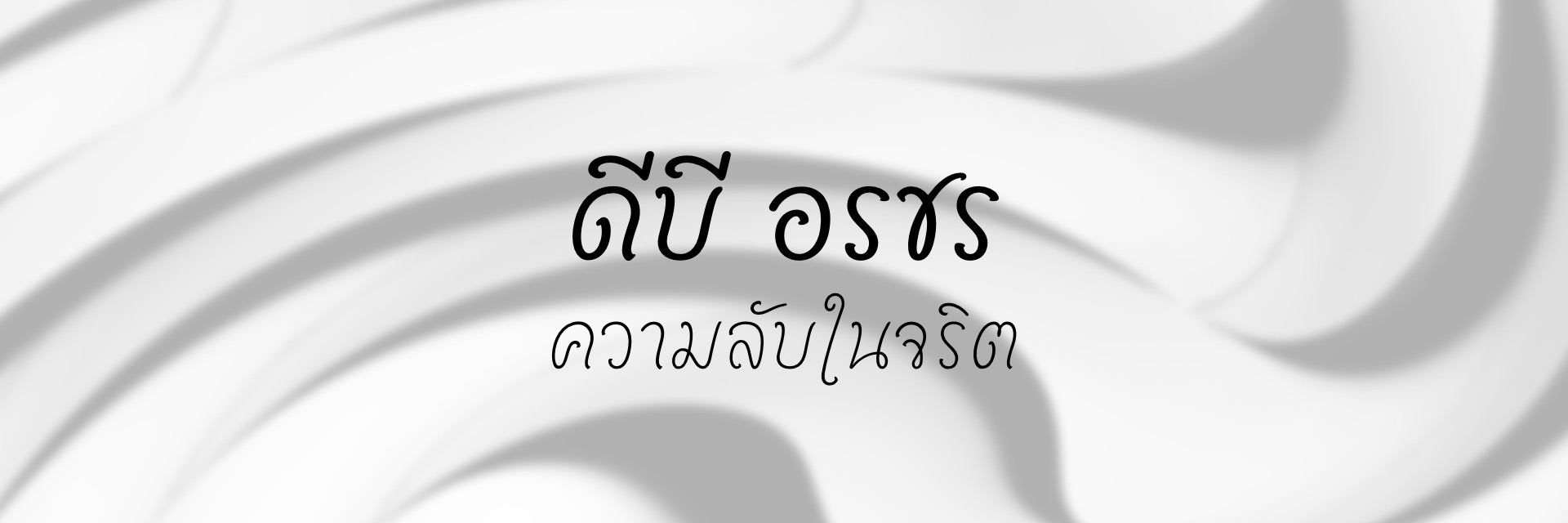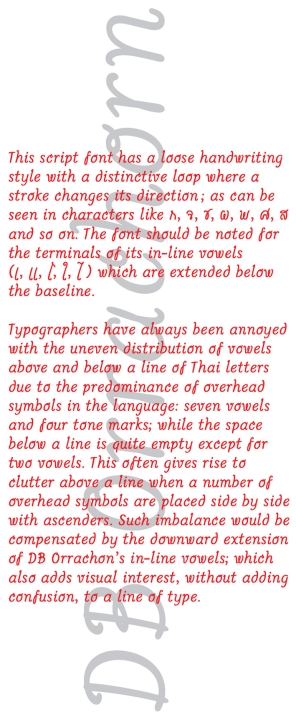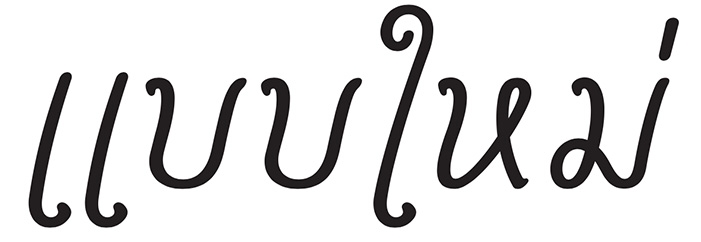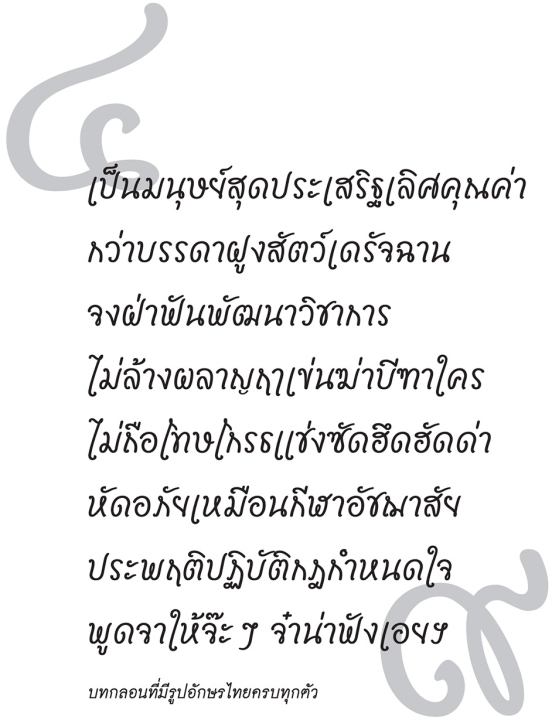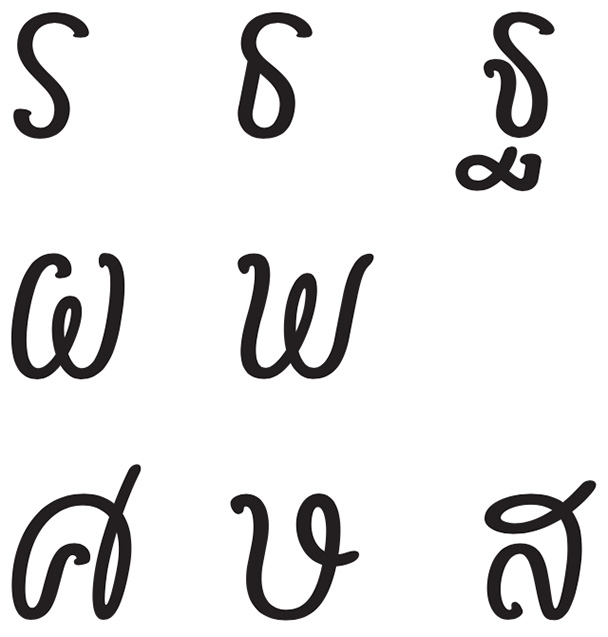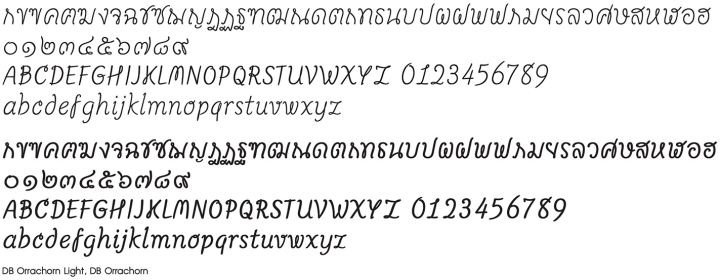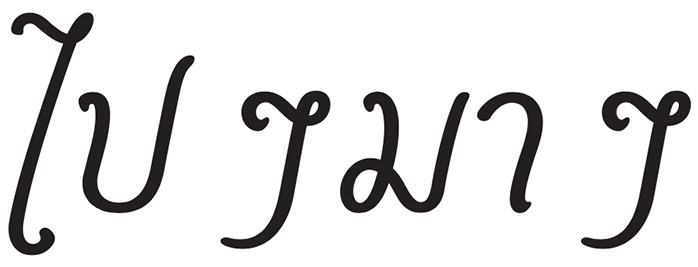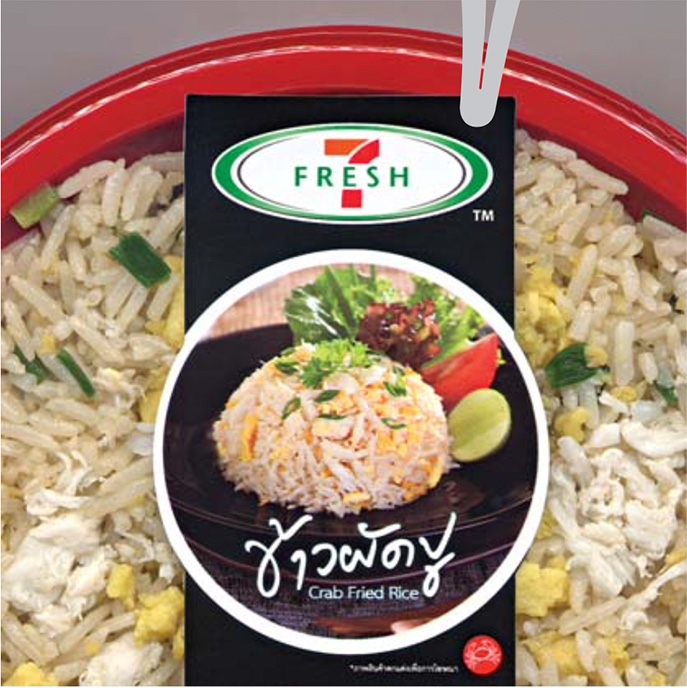
ซองยา ‘ทัมใจ’ Trademark ปัจจุบัน เขียนไม่ต่างจากชื่อเดิมที่ชื่อ ‘ทันใจ’ นัก
ตัวอักษรคําว่า ‘ทันใจ’ ในซองยาแก้ปวดที่ผมเห็นมาแต่เด็กจําได้ว่าอยู่มาวันหนึ่งชื่อต้องเปลี่ยนเป็น ‘ทัมใจ’ และใช้มาจนถึงปัจจุบันเพราะไปขัดกับกฎหมายไทยข้อที่ว่า ห้ามตั้งชื่อยาในเชิงโฆษณาสรรพคุณ. ลักษณะการเขียนคําว่า ‘ทันใจ’ เดิมเป็นเส้นอ่อนช้อย มีการขมวดในจังหวะที่เส้นเปลี่ยนทิศทางเป็นจุดเด่นที่สังเกตได้ชัด. เมื่อเปลี่ยน เป็น ‘ทัมใจ’ นั้น คนซื้อแทบไม่เห็นความเปลี่ยนแปลงเลย เพราะตัว ม ถูกพยายามทําให้ก้ำกึ่งระหว่าง ม กับ น โดยมีขมวดม้วนที่ฐานทั้งหน้าและหลัง เพียงแต่ขมวดม้วนใหญ่กว่าเพื่อให้ออกเสียงเป็น ม เท่านั้นเอง!
ตามประสาเด็กที่ริอ่านทําอะไรแบบผู้ใหญ่ ผมชอบสังเกตลายมือพี่ๆ ลายมือคุณครูบนกระดานที่เขียนได้รวดเร็ว แล้วลักจําเอามาลองหัดเขียนดูบ้าง (โดยมากเป็นตัวเอนขวา). จําได้ว่าทั้งหางตัว ศ ษ และ ส จะเขียนต่อ เนื่องโดยไม่ยกปากกา. ตัว ก นิยมเขียนเส้นหน้าเป็นเส้น ตรงขึ้นไปแล้วขมวดมุมเล็กๆ เป็นปมตวัดโค้งลงมาที่ฐาน. ส่วนตัว ย จะกลับกันกับ ก คือ จากหัวตวัดโค้งลงมาขมวดปมที่ฐานแล้วลากเป็นเส้นตรงขึ้นไป. เส้นที่ขมวดบนซองยาแก้ปวดและบนกระดานดําในลายมือหวัดที่เป็นครูของผมดังกล่าวมาได้กลายเป็นแรงบันดาลใจให้ผมคิดประดิษฐ์ตัวพิมพ์ลายมือไทยขึ้นมาใหม่โดยมีโจทย์สําคัญว่าทําอย่างไร ให้ดูร่วมสมัยขึ้น?
โฆษณาน้ําหวานตราสิงห์ ของบุญรอดบริเวอรี่ (พ.ศ.2483) สังเกตพาดหัวคําว่า ‘ไม่’ และ ‘เหมาะ’ คําแรกของบรรทัด
เขียนสระหน้าด้วยขนาดใหญ่เลยเส้นฐานลงมา
ผมลองค้นคว้าตัวลายมือเขียนตามสื่อโฆษณาสิ่งพิมพ์เก่าๆ ดูเพิ่มเติมเพื่อหาลูกเล่นดีๆ ที่อาจพอมีโอกาสปรับมาใช้ร่วมกันได้. ปรากฏว่าลายมือประดิษฐ์ที่สร้างแรงบันดาลใจให้ผมมากที่สุดก็คือกลุ่มที่เขียนสระหน้ายาวเลยเส้นฐานลงไป! ผมเคยตั้งข้อสังเกตไว้นานแล้วเมื่อตอนออกแบบฟอนต์ไทยใหม่ๆ ว่าแต่ละแถวตัวอักษรที่พิมพ์นั้นจะหนักบนมากกว่าล่าง เพราะภาษาไทยเรามีรูปวรรณยุกต์รวมการันต์อยู่ถึง 5 รูป วางอยู่บนตัวอักษร อีกทั้งรูปสระบนที่ใช้ประจําอีก 7 รูป (รวมสระ อํา เข้าไปด้วย) ขณะที่มีรูป สระล่างอักษรเพียง 2 รูปเท่านั้น ถ้าเราลองเทียบดูกับตัว script ของฝรั่งที่นิยมเขียนตัว f ต่ำเลยฐานลงมา จะพบว่าสัดส่วนจํานวนตัวอักษรที่มีรูปเกิน x-height ขึ้นไป ต่อจํานวนอักษรที่มีรูปล้ำเลย baseline ลงมา มีค่าเท่ากับ 7 : 6 (จุค i, j เล็กๆ ไม่นับ) ตัดตัว f ที่มีรูปล้ำทั้งบนและล่างทิ้งก็จะเป็น 6 : 5 ถือว่าสูสี. ถ้าคิดความถี่ในการใช้งานจริง เช่น j, q มีที่ใช้น้อย ตัดทิ้ง 2 ตัว ก็จะเป็น 6 : 3 หรือ 2 : 1. เมื่อเทียบกับลายมือเขียนของไทยดูยังไงก็ต้องมากกว่า 2 : 1 (ใครไม่เชื่อลองค้นหา เอาค่าเฉลี่ยความถี่ในการใช้งานมาคํานวณดูเองก็ได้)
ด้วยเหตุนี้ การเขียนสระหน้าให้ห้อยต่ำกว่าเส้นฐานลงมาจึงน่าจะเป็นหนทางใหม่ที่ช่วยปรับสมดุลความเข้ม ระหว่างบนและล่างแถวตัวอักษรลายมือเขียนไทยให้เฉลี่ยใกล้เคียงกันมากขึ้น.
เมื่อความคิดตกผลึกแล้ว ผมหาช่วงเวลาสบายๆ เขียนชุดตัวอักษรในจินตนาการออกมาด้วยปากกาลูกลื่นบนกระดาษ มันเสร็จลงอย่างรวดเร็วอย่างไม่น่าเชื่อ. เคล็ดลับก็คือผมไม่ได้ค่อยๆ ร่างทีละตัวเป็นกลุ่มๆ ตามลักษณะความคล้ายคลึงกันเหมือนตอนร่างแบบตัวพิมพ์เนื้อเรื่อง (text) หรือตัวพิมพ์หัวเรื่อง (display) ที่เคยทําผ่านๆ มา. ลายมือเขียนจะดูเป็นธรรมชาติก็ต้องเกิดจากการเขียนเนื้อความต่อเนื่องไปเรื่อยๆ. ผมเลือกเอากลอนพิเศษ 2 บทที่มีคนแต่งไว้ให้ใช้รูปอักษรไทยครบทุกตัวนํามาเขียนด้วยอารมณ์ไหลลื่น. มันไม่เชิงเป็นลายมือหวัด เพียงแต่เอาวิธีการเขียนหวัดที่ชอบขมวดม้วนแบบโบราณมาเขียนให้ละเมียดขึ้นด้วยการเขียนให้ช้าลง เหมือนเอาเพลงเร็วมาเปลี่ยนจังหวะใหม่ให้ช้าลง เพื่อมีเวลาพอที่จะเพิ่มเสียงเอื้อนเข้าไป. เบื้องหลังของการเขียนต้นแบบฟอนต์ตัวนี้ที่สําคัญมีอยู่ 3 เรื่อง คือ การขมวดม้วนเส้น, การเปลี่ยนทิศทางของการเขียน, และการเปลี่ยนรูปอักษร.
การเขียนขมวดนั้นถือเป็นจุดเด่นสําคัญประการหนึ่งที่มีพบอยู่ทั่วไป. ความยากคือ การตัดสินใจเลือกใส่จริตแต่พองาม. ตัว ก และอักษรคล้ายของมันซึ่งมีมาก ผมเลือกขมวดที่ปากทุกตัวให้เกิดช่องว่างเน้นๆ เป็นการคุมสไตล์. ส่วนตัว ข เลือกที่จะไม่ขมวดเลย ไปเน้นขมวดอ้วนๆ ที่ตัว ช แทน เพราะลองเขียน ข แบบขมวดที่ฐานให้เกิดช่องว่างดู ถึงหางจะสั้นก็มีโอกาสดูสับสนเป็นตัว ช ได้.
ตัว จ ผมเขียนเลียบแบบ จ จากซองทันใจ ในความทรงจําวัยเด็ก. ตัว ง ผมไม่เขียนแบบ จ เพราะรู้สึกฝืน. เช่นเดียวกัน ตัว ล ผมก็ไม่ขมวดม้วนแบบตัว จ ที่ฐาน เพราะเล็งที่จะขมวดหางเป็น ส อยู่แล้ว (ถ้าเขียน ส ขมวด ทั้งล่างและบน จะต้องฝืนเขียนและดูรุงรัง). ส่วนตัว ฐ ถ้าเขียนแบบตัว จ จะทําให้ต้องขมวดหางแบบตัว ส รวมกับ ขมวดที่เชิงเข้าไปคงเปรอะเกินไป จึงเลี่ยงเขียนเป็น s-curve แบบตัว ร ซึ่งดูร่วมสมัยกว่า.
ตัว ผ, พ และตัวคล้ายของมันผมเน้นขมวดกลางตัวให้เกิดช่องว่างไปเลย. ส่วนพวกหัวหยัก เช่น ฆ หรือเส้นบนหยัก เช่น ต นั้น แค่ขมวดเป็นมุมตันๆ ไว้ก็พอ. ในตัวเลขไทยก็เช่นกัน ขมวดตันพบอยู่ได้ทั่วไป ยกเว้นที่ฐานของเลข ๔, ๕ และที่เส้นทะแยงของเลข ๙ จะเน้นขมวดให้เกิดพื้นที่ว่าง. ส่วนวรรณยุกต์ตรี (ที่รูปคล้ายเลข ๗) และไม้ไต่คู้ (ที่รูปคล้ายเลข ๘) ตั้งใจเขียนให้มีขนาดเล็กแบนเพื่อปรับสมดุลไม่ให้เหนือตัวพยัญชนะดูเข้มไป จึงต้องลดการม้วนไปโดยปริยาย.
ระหว่างที่ผมเขียนด้วยลูกลื่นนั้น ผมจินตนาการว่ามือกําลังถือพู่กันจุ่มสีเขียนอยู่. เมื่อต้องเขียนสระหน้ายาวๆ ล้ำเส้นฐานลงมาให้พริ้วหวานเป็นธรรมชาตินั้นการเขียนต้องเป็นไปตามธรรมชาติด้วย. เคล็ดลับก็คือผมเขียนจากบนลงล่างนั้นเอง (ถ้าไม่เชื่อลองเอาพู่กันเขียนสระหน้า ยาวๆจากหัวขึ้นไปดู), การเขียนสระหน้าแบบนี้แท้จริง เกิดจากการจงใจเปลี่ยนรูปอักษรก่อน.
ใบปิดถ้วยข้าวผัดปู 7 FRESH ของเครือ ซี.พี. ถ้าเขียนคําว่า ‘เข้าแล้ว’ ด้วยลายมือเขียนแบบเดียวกันนี้ อาจอ่านผิดเป็น ‘เช้าแล้ว’ ก็เป็นได้
หลักการสําคัญของการเปลี่ยนรูปอักษรที่ผมใช้ประจําก็คือ ต้องไม่ส่งผลต่อการอ่าน. จะเห็นได้ว่าสระหน้าที่ยาวเลยฐานลงมาดูยังไงก็ไม่สับสนกับตัวอักษรอื่นๆ อยู่แล้ว. ผมลองเล่นคลื่นที่ส่วนบนของไม้มลายแล้วขมวดมุมทึบก่อนลากลงมา พบว่ามันน่าสนใจดี จึงขยายผลต่อไปที่ตัวไม้ยมก (ๆ) แต่คราวนี้ขมวดเน้นพื้นที่ว่างแทน เพราะเห็นว่านานๆ ใช้ทีเลยเอาเสียหน่อย. แม้ว่าการเขียน ไ, ๆ ของผมจะแตกต่างไปจากมาตรฐานเดิม แต่ยังคงอ่านได้สบายไม่สับสนกับตัวอื่น.
ตัว script ฝรั่งถูกเขียนขึ้นให้เข้ากับลายเขียนไทยด้วยปากกาลูกลื่นเช่นกัน. ผู้ช่วยของผมเพิ่มน้ําหนักเส้นเข้าไปให้ดูคล้ายเส้นพู่กันในคอมพิวเตอร์จนได้ออกมาอย่างที่เห็น. ถือเป็นตัวพิมพ์ลายมือวาดแบบอ่อนช้อยที่ช่วยชะลอกระแสโลกที่รีบเร่งและร้อนแรงให้ผ่อนคลายลง. มันดูต่างจากลายมือปรกติของผมซึ่งดูหวัดกว่านี้ เพราะมักต้องรีบเขียนเพื่อเก็บความคิดไว้ให้ได้ทันก่อนจะหายวับไป! ด้วยความที่มันดูไทยๆ ดี ผมจึงคิดหาทางตั้งชื่อเป็นคําไทยๆ ที่สามารถอธิบายลักษณะของตัวพิมพ์ได้อย่างเหมาะสม.
ในที่สุดผมตัดสินใจให้ชื่อฟอนต์ชุดนี้ว่า ‘อรชร’ เพราะนอกจากจะแสดงภาพลักษณ์ของฟอนต์ได้ดีแล้ว ยังเป็นชื่ออาคารเรียนของผมสมัยอยู่ปีหนึ่งเตรียมอุดมฯ พญาไท ผมอยู่ห้อง 1 ตึกอรชร 3 ห้องนี้มีชื่อเรียกอีกชื่อว่าห้องสิ่งประดิษฐ์ 1. นี่คือความลับของความหมาย
‘อรชร’ ก็คือ สิ่งประดิษฐ์ ที่ผ่านการประดิษฐ์ประดอยให้อ่อนช้อยนั่นเอง.